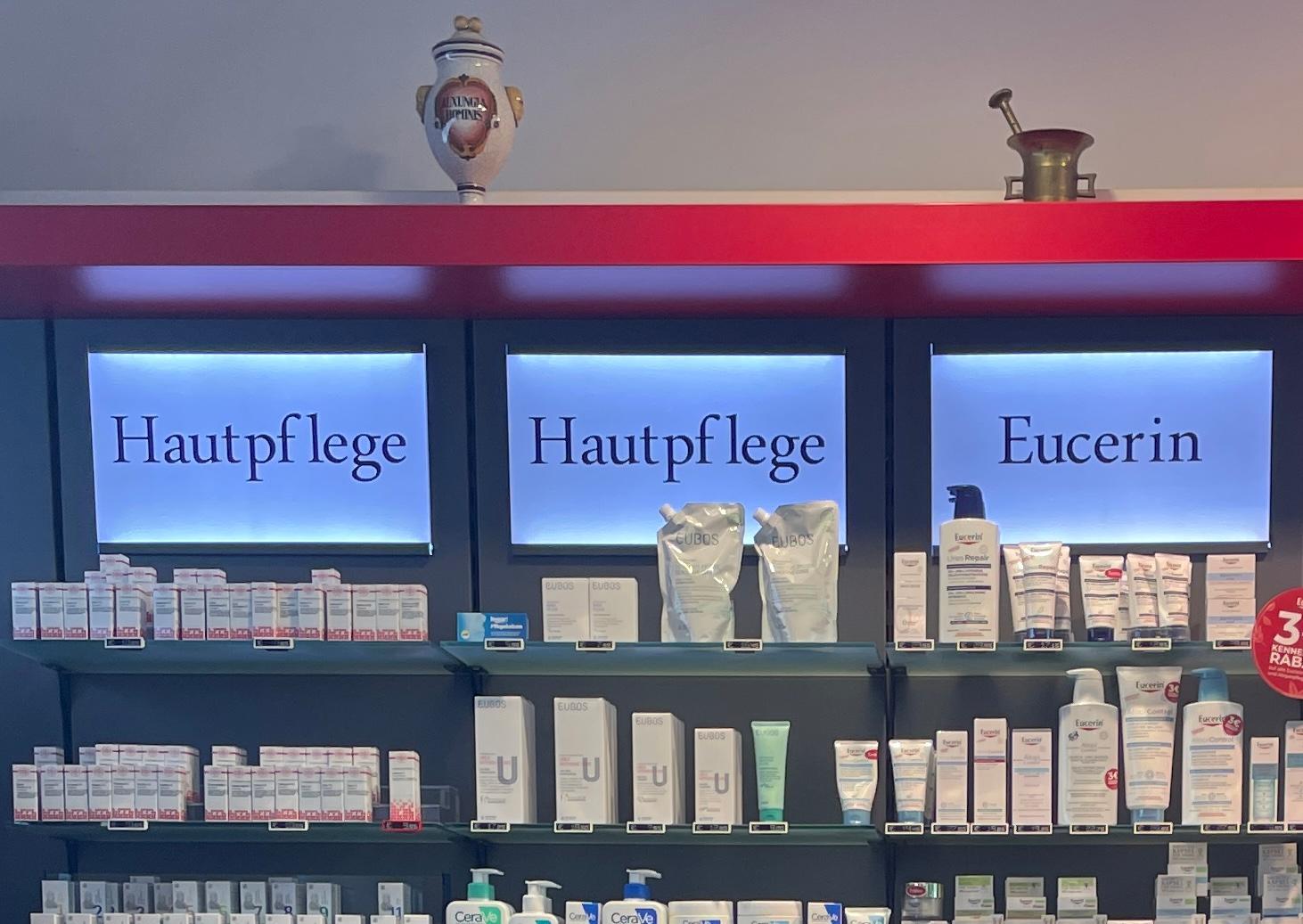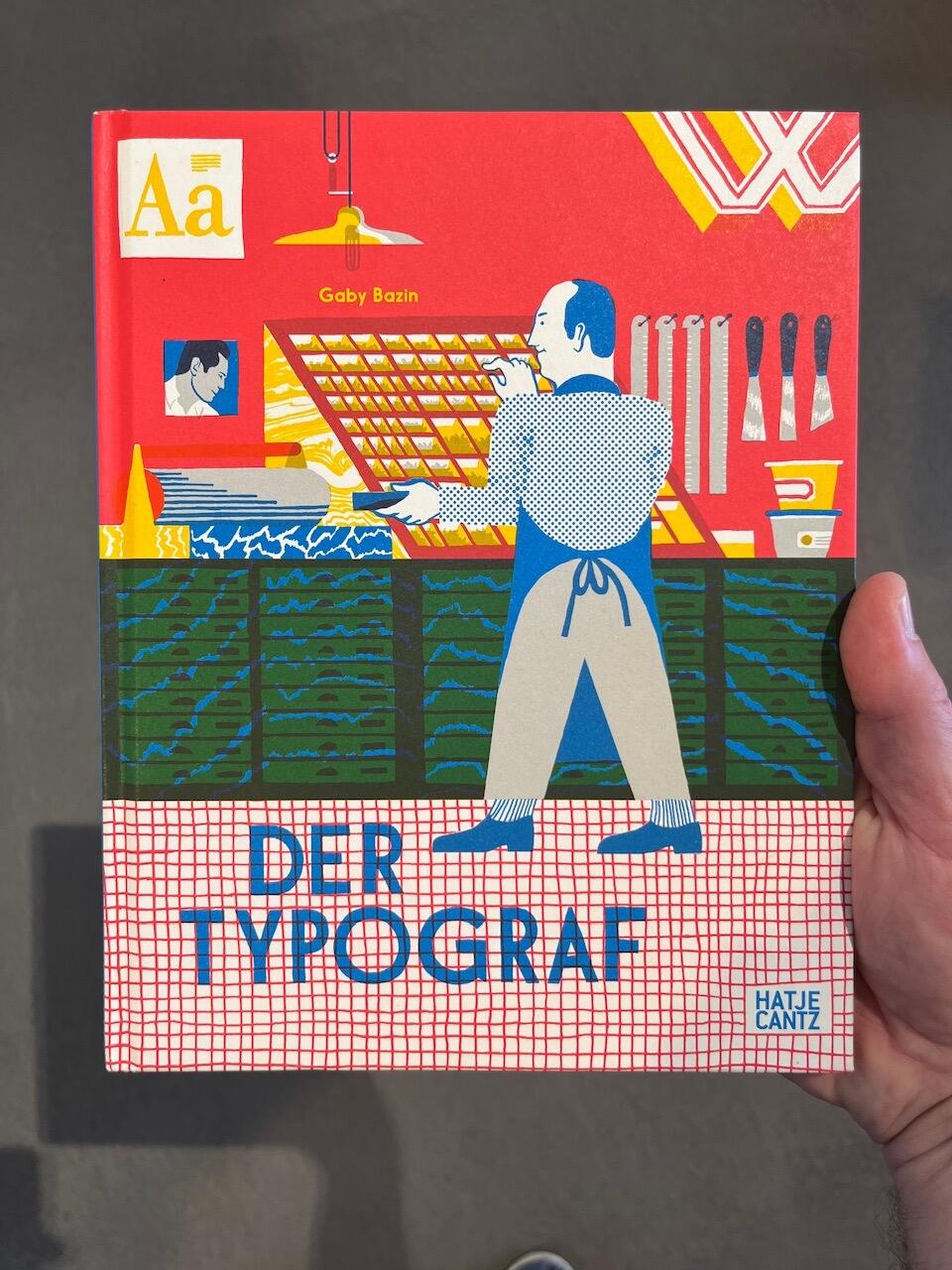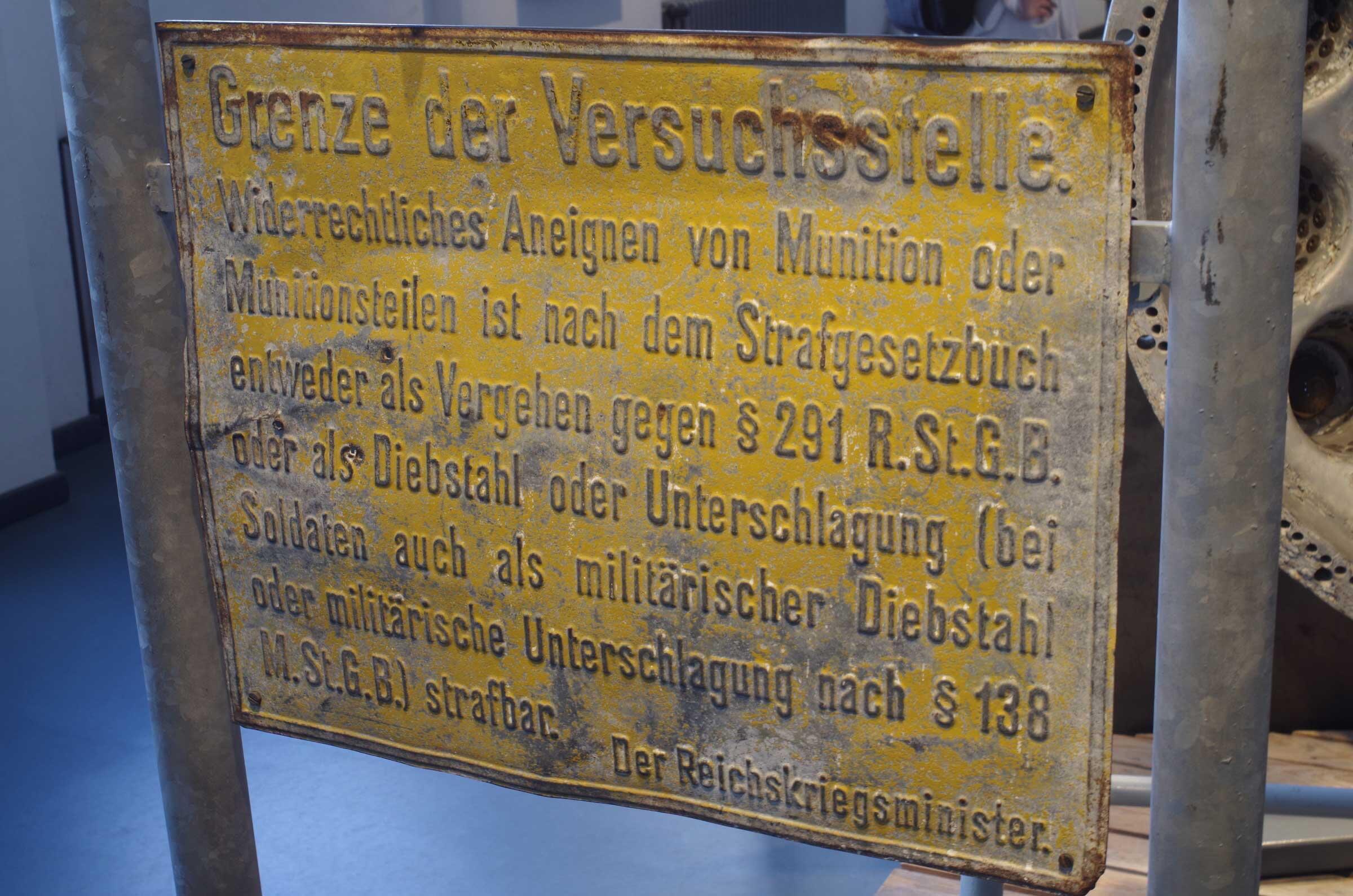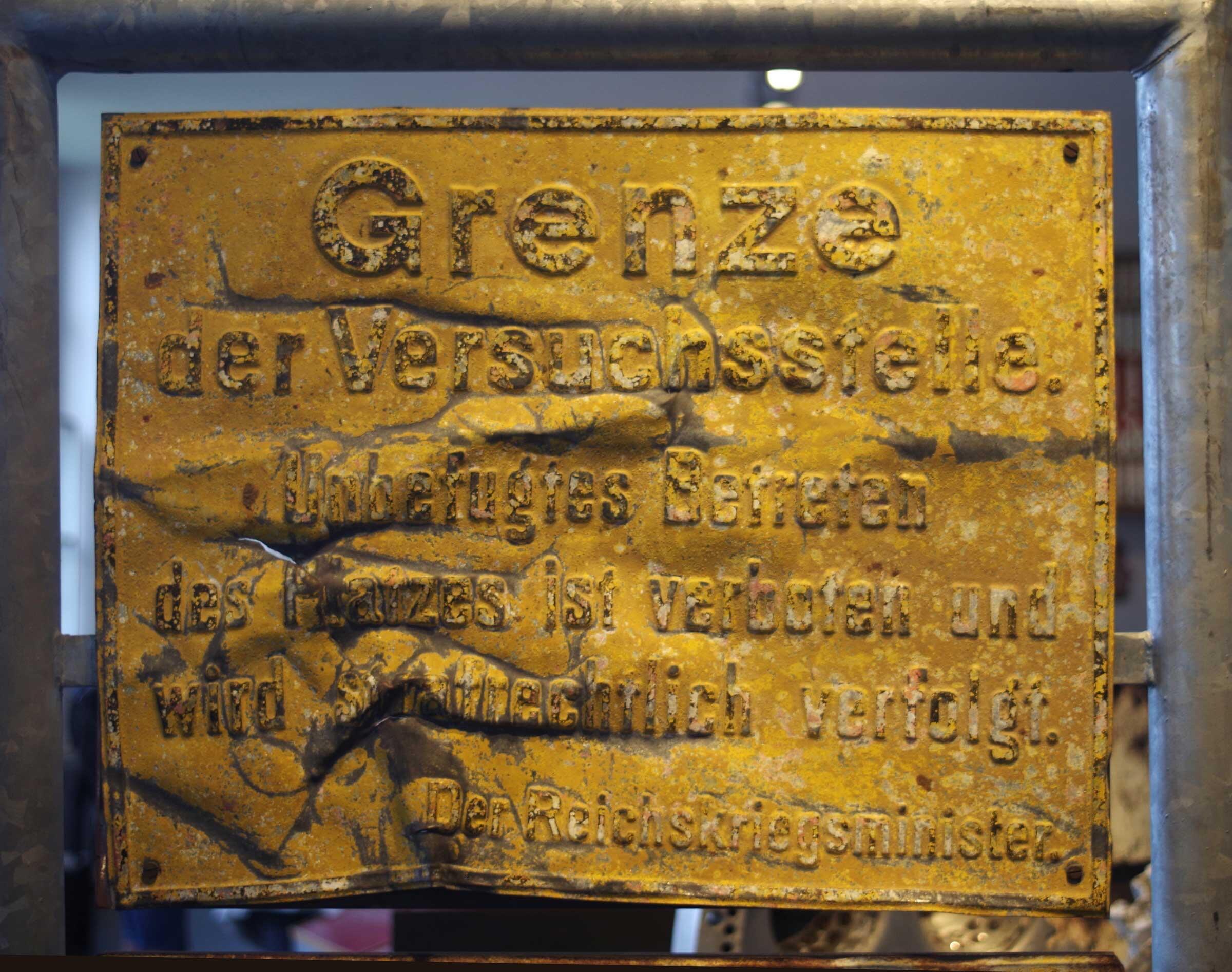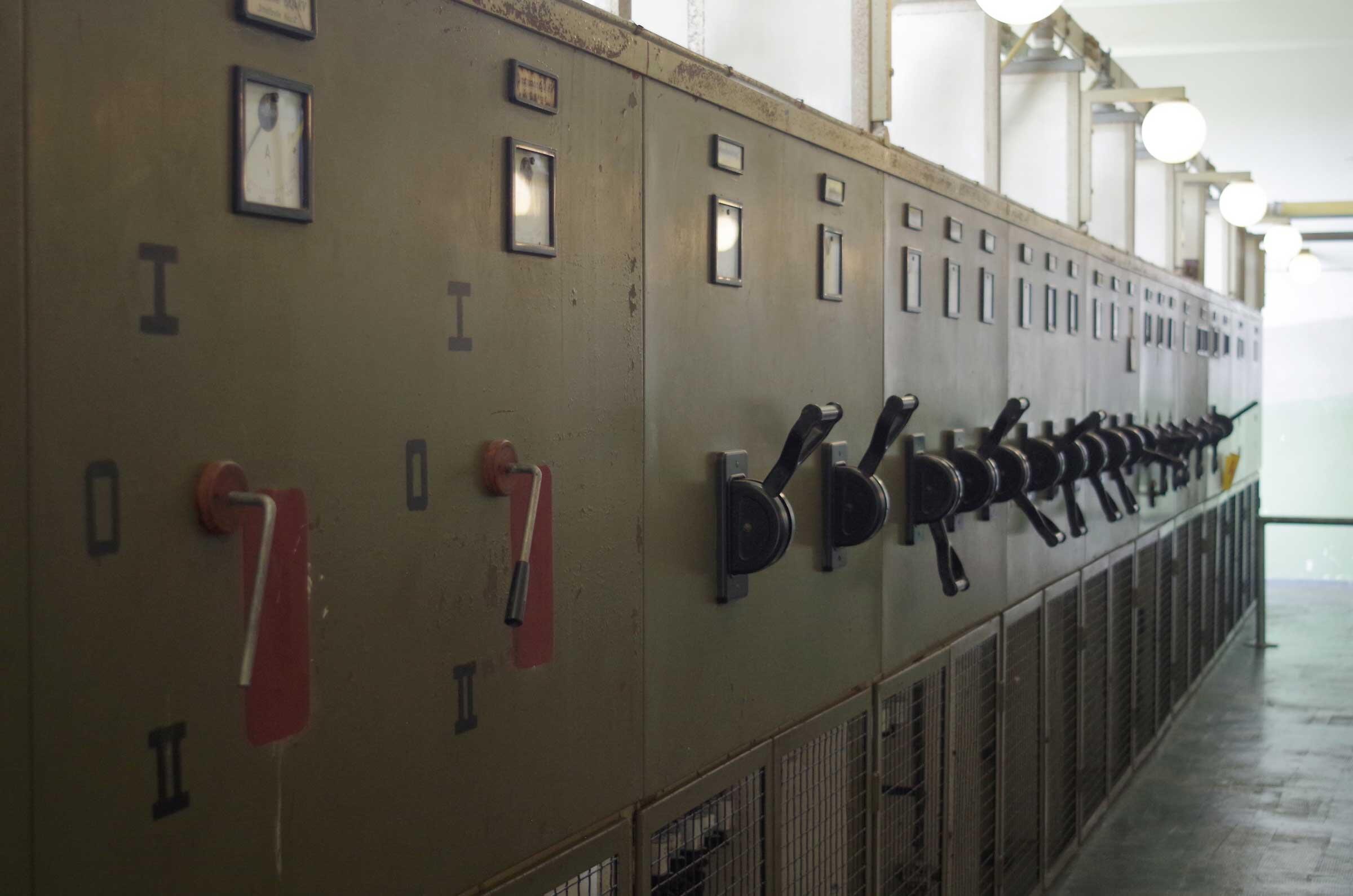
Irritiert...
Die Lettern habe ich vor ein paar Jahren in einer Mudlarker-Ausstellung anschauen können. Ich war zufällig gerade in London und bin nach Feierabend dorthin geteilt. Ich war gespannt und wurde enttäusch: Die Lettern waren lausig und unscheinbar präsentiert – ein Häufchen Metall in einer kleinen Schale in einer Vitrine. Unscheinbar und aber zu finden zwischen Pfeifenköpfen, Zahnprothesen und Mantelknöpfen. Kein Quatsch.
Eine Etage höher in einer anderen Vitrine – auch nur zwischen Unrat – lag eine ausgedruckte Glyphentabelle und darauf waren nochmal ein paar Lettern hingestreut. Das war es.
Zumindest ein Schild war in der Doves gedruckt.
Ich hatte Robert Green seinerzeit gefragt, ob er ein ẞ zufügen würde. Wollte er, aber ich fürchte, das ist untergegangen. Werde mal nachschauen.
Das Pub, in dem die Gründung der Doves Press beschlossen wurde, heißt Doves, ist über 300 Jahre alt und man kann noch immer ein Ale dort trinken – mit Blick auf die Themse. Und mit dem Wissen um die Doves Press ist das ein ziemlich cooles Gefühl, dort zu sitzen
Das Gebäude in dem die Doves Press war, steht zwei Häuser weiter, ist aber nicht zugänglich.
Exponate des Historisch-Technischen Museums Peenemünde, und ein Bild aus der Schaltzentrale … (des ehemaligen Kraftwerks Peenemünde, wo sich das heutige Museum befindet)
Fehler bei der Hautpflege – damit alles geschmeidig bleibt ;-)
Hautpflege
Das ist gleich die Anwendung beschrieben:
»Auf die Haut – Quetschgeräusch »pf« –  legen«
Etwas mehr Abstand zwischen Pünktchen und A wäre noch hübscher gewesen.